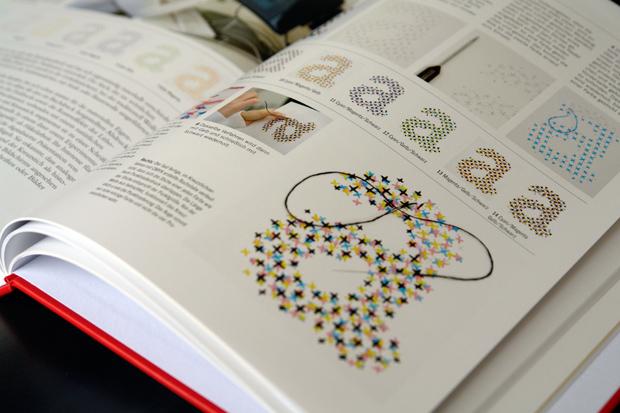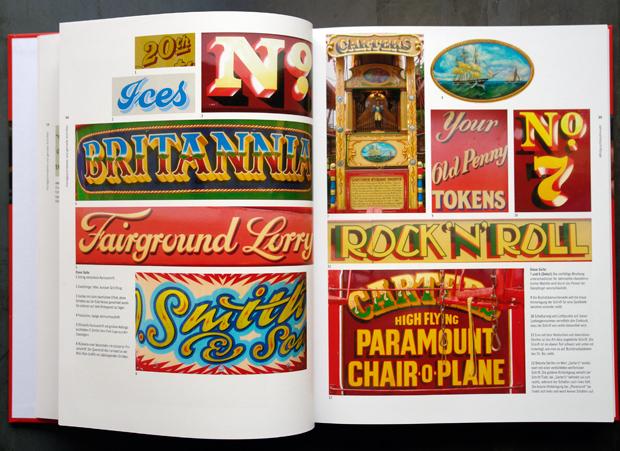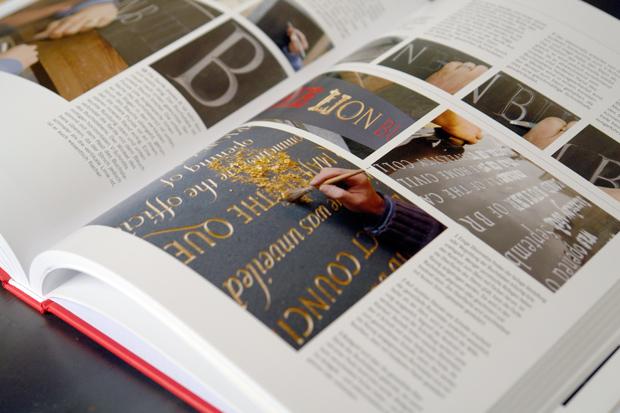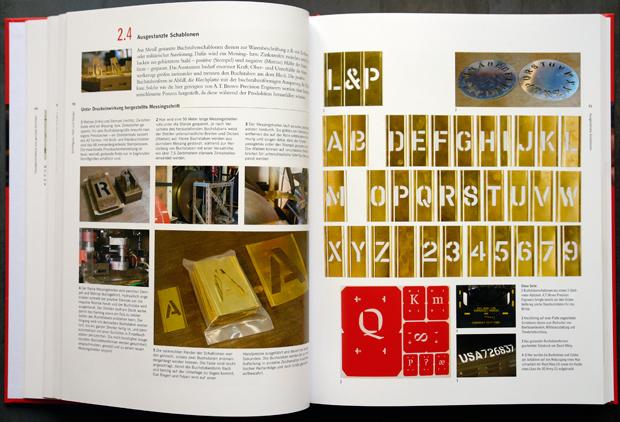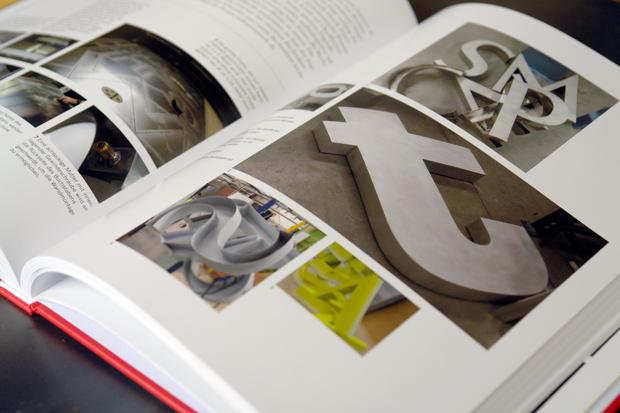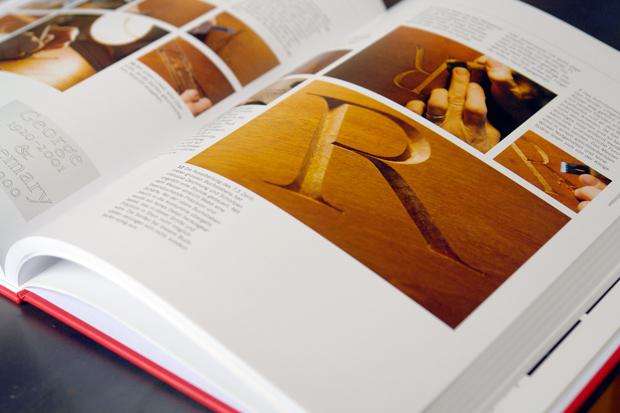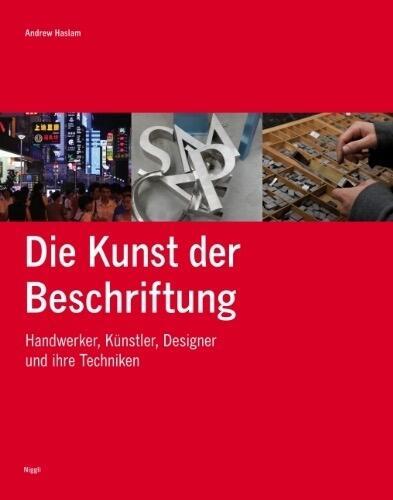
»Die Kunst der Beschriftung« stellt mit kurzen, erläuternden Texten und zahlreichen Fotos die Herstellungsprozesse von mehr als achtzig Beschriftungsverfahren vor. Ergebnis ist ein Kompendium klassischer und aktueller Wege, Schrift herzustellen und anzuwenden.
Das Buch »Die Kunst der Beschriftung« aus dem Niggli-Verlag ist die deutsche Ausgabe des englischen Buches Lettering: A Reference Manual of Techniques von Andrew Haslam. Der Autor ist Absolvent des Royal College of Art in London und neben seiner publizistischen Tätigkeit als Dozent für Grafikdesign und Typografie an mehreren britischen Universitäten tätig. Für dieses Buch besuchte er zusammen mit einem Fotografen Handwerker, Künstler und Betriebe und dokumentierte ihre Arbeiten und Techniken.
Das Buch beginnt mit einer Einführung in typografische Grundbegriffe zur Buchstabenanatomie sowie typografischen und technischen Fachbegriffen aus dem Schriftsatz. Diesen Teil des Buches sollte der Leser besser gleich überblättern, da sich hier zu viele Fehler und teils haarsträubende Aussagen finden. Wahrscheinlich hat wohl auch die Übersetzung ihr Übriges dazu beigetragen, dass die Erläuterungen falsch oder zumindest für den Leser unverständlich erscheinen. Für typografische und technische Grundlagen dieser Art seien hier Anatomie der Buchstaben* und Decodeunicode empfohlen.
Die folgenden sechs Kapitel widmen sich dann den einzelnen Beschriftungsverfahren. Die Kapitel heißen:
• Handgeschrieben und gemalte Schriften
• Schriftguss, Satz und Design
• Druck
• Geschnitzte, gravierte, geätzte und dreidimensionale Buchstaben
• Geformte und gegossene dreidimensionale Schrift
• Buchstaben in Textilien
• Leuchtschrift, Animation und Bewegtgrafiken
Jedes Schreib-, Druck-, Produktions- oder Beschriftungsverfahren ist mit einer Einleitung mit generellen und entwicklungsgeschichtlichen Informationen versehen und dann mit einer bebilderten Schritt-für-Schritt-Abfolge des tatsächlichen Beschriftungsprozesses dargestellt. Beachtlich ist der gewählte Umfang der Verfahren. Neben den klassischen Schriftsatz- und Druckverfahren kommen selbst Anwendungen wie essbare oder gestickte Buchstaben, Tattoos, Kanalbootbemalungen sowie Buchstaben als Feuerwerksinstallation zur Sprache. Wer für anstehende Projekte noch Inspirationen für ausgefallene typografische Anwendungen und Veredelungstechniken sucht, wird in diesem Buch sicher fündig.
So ist die Stärke des Buches sicherlich vor allem, dass die beschriebenen Techniken alle im tatsächlichen Herstellungprozess in Werkstätten und Betrieben dokumentiert wurden. Insofern hat dieses Kompendium sicher auch dann noch einen großen Wert, wenn die beschriebenen Techniken zukünftig veraltet sein werden und außer Gebrauch geraten sind. Und jeder, der sich für Typografie begeistern kann, wird sicherlich allein an den über 1000 Detailaufnahmen im Buch große Freude haben.
Klar sollte allerdings auch sein, dass das Buch seine Herkunft aus Großbritannien nicht verleugnen kann – und natürlich auch nicht muss. Die vorgestellten Techniken dokumentieren die Anwendung lateinischer Schrift in ganz bestimmten Betrieben und Werkstätten in Großbritannien und die Inhalte spiegeln somit nicht unbedingt immer allgemeingültig das Wissen und die Anwendung in den jeweiligen Fachbereichen wider.